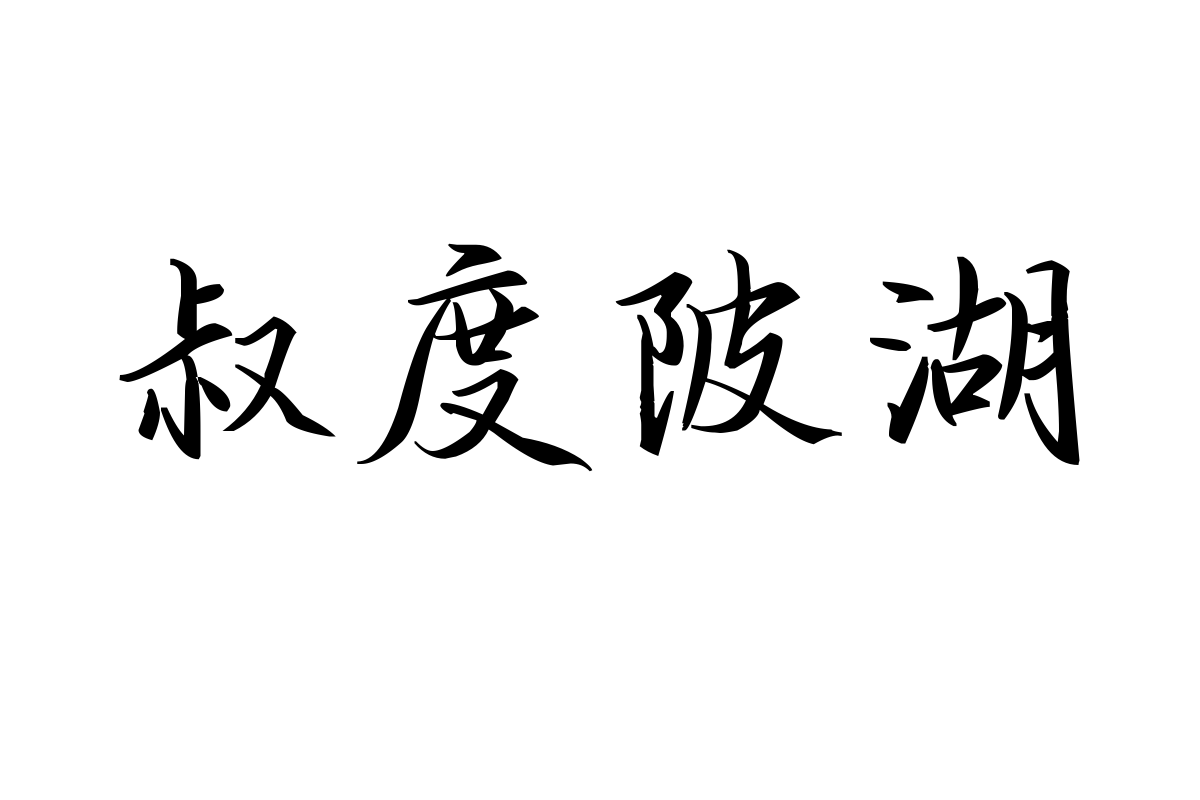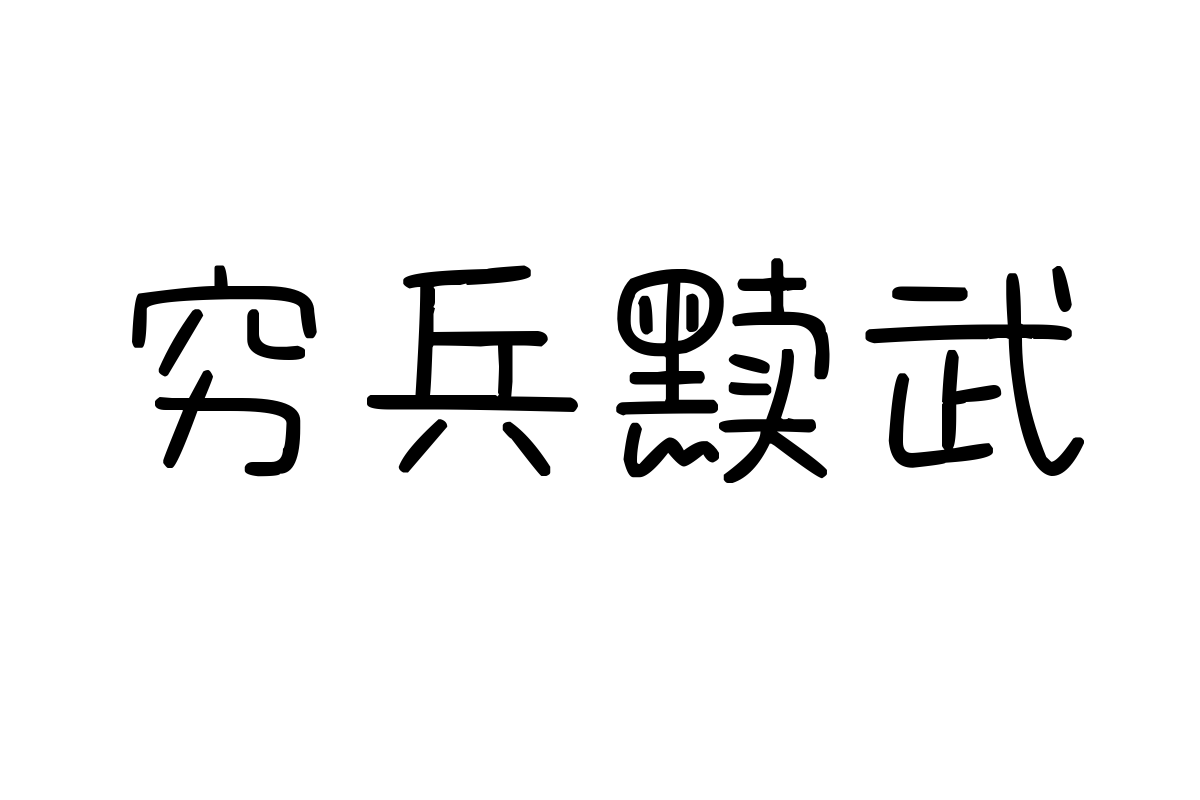
也字工厂幼稚园体是一款专为儿童设计的字体,其特点是字形圆润可爱,笔画简单易学,适合幼儿学习和书写。这款字体采用了可爱的卡通风格,使得孩子们在书写时能够更加愉悦和自信。同时,也字工厂幼稚园体还注重保护视力,采用无衬线设计,减少了视觉疲劳。总的来说,也字工厂幼稚园体是一款非常适合幼儿使用的字体,既美观又实用。
字体结构紧凑,笔画流畅自然,给人一种轻松愉悦的感觉。同时,也字工厂川秋沙行楷还注重细节处理,每个笔画都经过精心设计,使得整体效果更加和谐统一。
无论是用于印刷品还是电子屏幕显示,也字工厂川秋沙行楷都能展现出其独特的魅力。它不仅能够提升设计作品的整体视觉效果,还能够增强读者的阅读体验。
总之,也字工厂川秋沙行楷是一款值得推荐的字体,无论是专业设计师还是业余爱好者,都可以在这款字体中找到属于自己的风格和灵感。